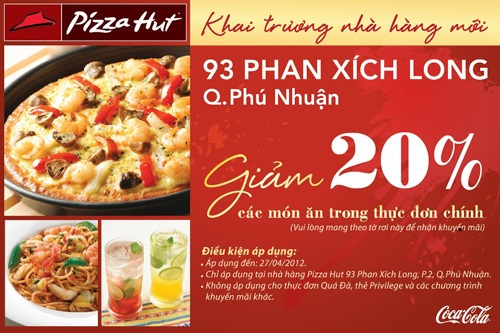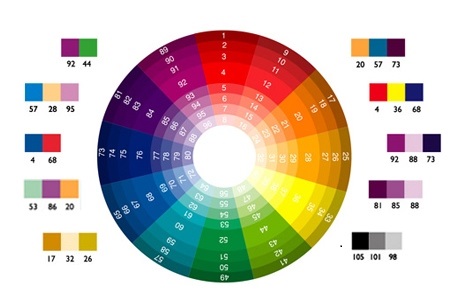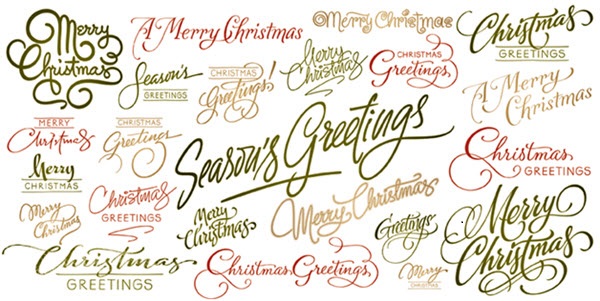
Tờ rơi đang ngày càng khẳng định tầm quan trọng của nó trong các chiến dịch quảng cáo. Việc thiết kế tờ rơi là công đoạn quan trọng bậc nhất khi sử dụng tờ rơi. Trong đó, màu sắc và font chữ trên tờ rơi sẽ quyết định mức độ chú ý của khách hàng đối với tờ rơi. Hãy cùng chúng tôi tìm hiểu về màu sắc và font chữ khi thiết kế tờ rơi.
Màu sắc chủ đạo là điểm đầu tiên quyết định xem tờ rơi có thu hút được ánh nhìn của khách hàng hay không? Màu sắc chủ đạo cần nổi bật, kích thích thị giác.
Màu sắc chủ đạo cần phù hợp, hài hòa với bộ nhận diện thương hiệu của doanh nghiệp, cửa hàng, … Từ đó, các màu sắc khác trên tờ rơi sẽ hỗ trợ màu sắc chủ đạo trong việc truyền tải thông điệp, nội dung.
Cần điều chỉnh độ bão hòa và sắc của màu chủ đạo để tờ rơi sáng hơn, đem lại hiệu quả tốt hơn.
Tùy từng loại tờ rơi cho các lĩnh vực khác nhau mà bạn nên lựa chọn màu sắc chủ đạo khác nhau. Các màu nóng thường được sử dụng nhiều nhất: đỏ, vàng, cam, … Những gam màu chủ đạo nên sôi động, mạnh mẽ, ấn tượng trong phổ màu sắc. điều này sẽ giúp làm nổi bật nội dung, tạo sự dễ tiếp thu thông tin cho khách hàng.
Bên cạnh đó, màu hình ảnh, màu chữ cũng cần đặc biệt lưu tâm để đảm bảo tính sáng tạo, tạo ấn tượng đối với khách hàng.
Đảm bảo tính dễ đọc của nội dung: Sử dụng kết hợp các font chữ cổ điển đan xen hiện đại. Hầu hết các font cổ điển được thiết kế rất kỹ lưỡng với sự chặt chẽ giữa các nét chữ, có tính dễ đọc rất cao
Không sử dụng quá nhiều font chữ trên tờ rơi: Nếu bạn sử dụng quá nhiều font chữ trên tờ rơi, ngược lại với mục đích tạo điểm khác biệt, tờ rơi sẽ trở nên rối mắt, gây khó khăn cho người tiếp nhận thông tin.
Sử dụng chữ in hoa, in thường hợp lý: Nội dung headline nên được in hoa, không nên in hoa tùy tiện. Chữ thường dễ đọc nhất, vì có những đường nét lên xuống bên trong nét chữ.
Size và đường nét của chữ phù hợp: Font chữ quá nặng sẽ tạo sự tương phản mạnh với nền làm nội dung trên tờ rơi trở nên khó đọc. Dùng font chữ có độ rộng trung bình, tránh dùng những font quá rộng hoặc quá hẹp